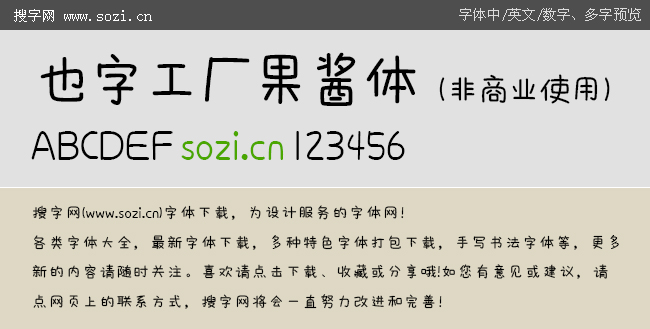
也字工廠果醬體
搜字網(wǎng)給大家提供一款也字工廠果醬體(非商業(yè)使用)中文字體下載,也字工廠果醬體是一款卡通字體,字體書寫可愛有趣,充滿童真。具有很好的視覺效果。適合應(yīng)用于藝術(shù)設(shè)計(jì)、平面宣傳設(shè)計(jì)、網(wǎng)頁設(shè)計(jì)、海報(bào)設(shè)計(jì)等應(yīng)用(此字體為個(gè)人非商用版,商用可以聯(lián)系:官方網(wǎng)址:https://yefont.com/home,聯(lián)系方式:13798980448)。